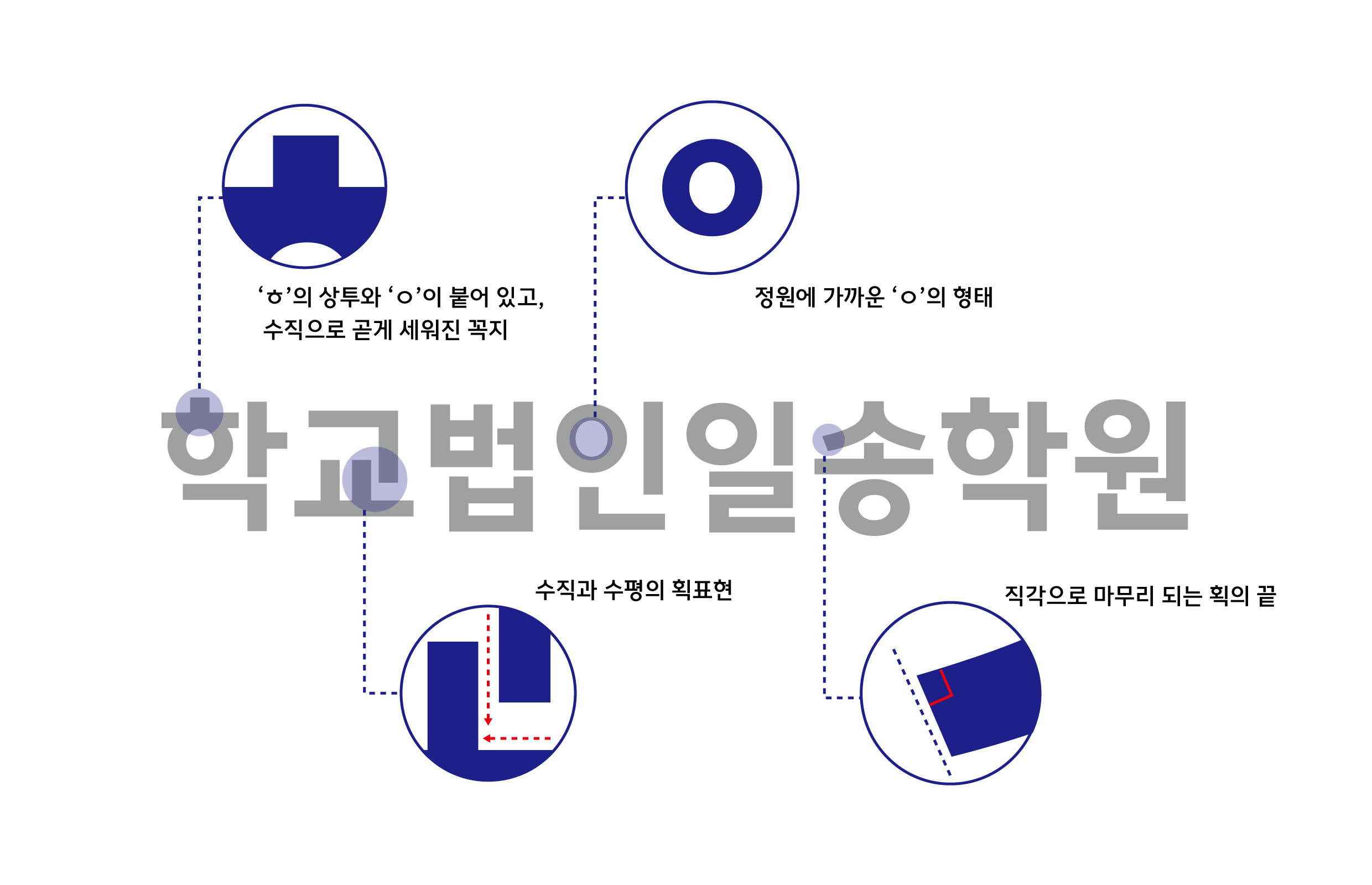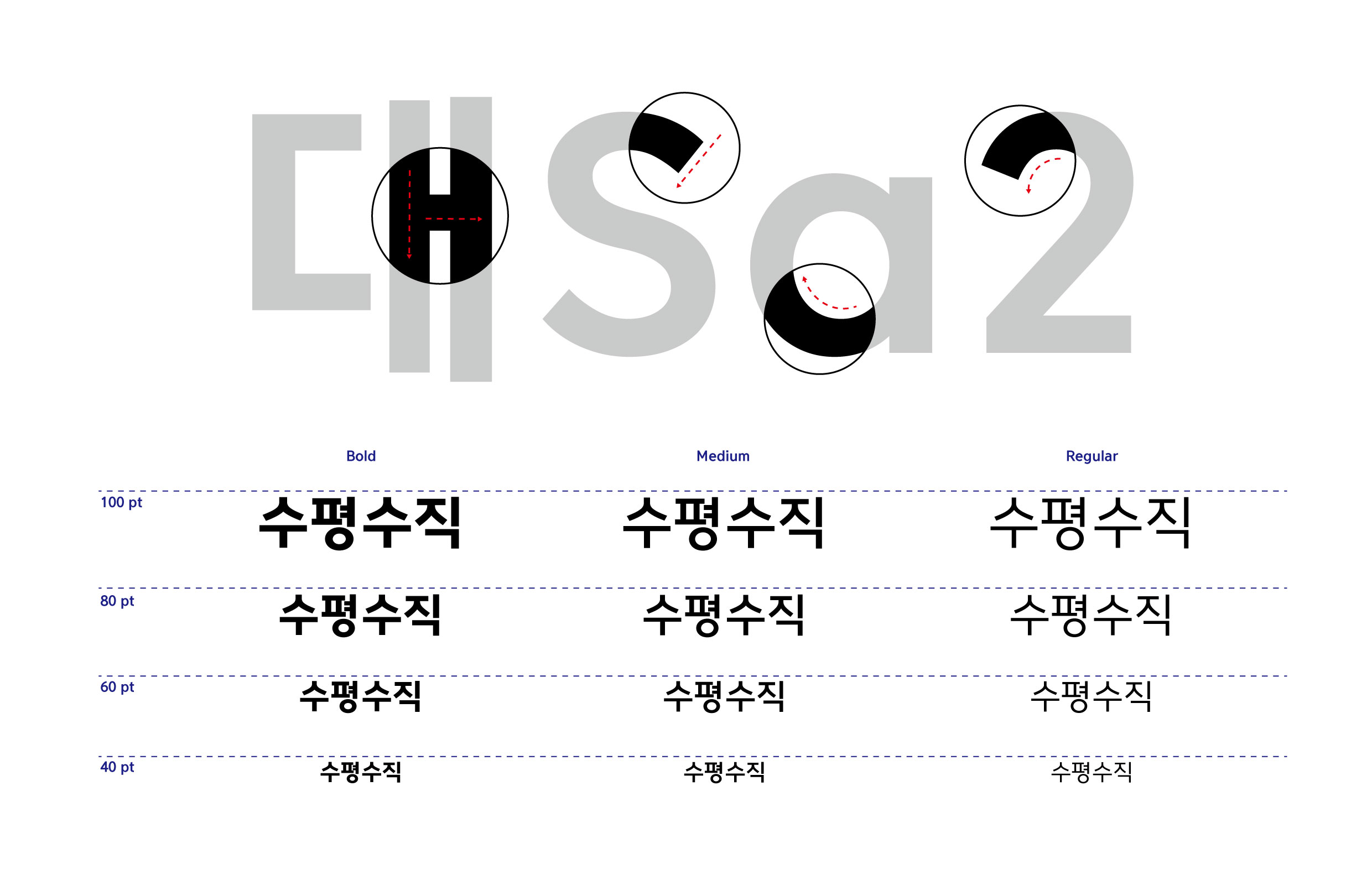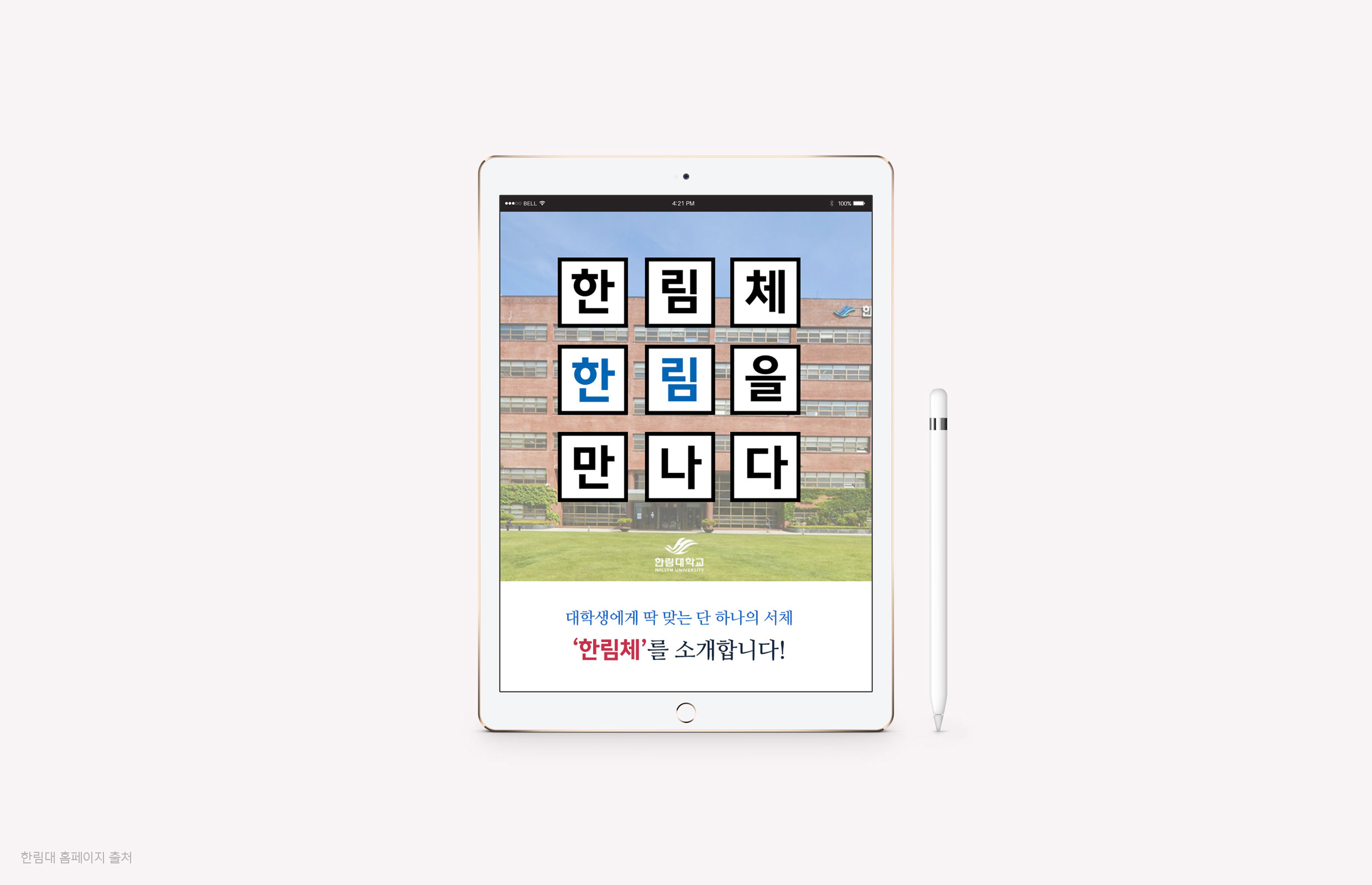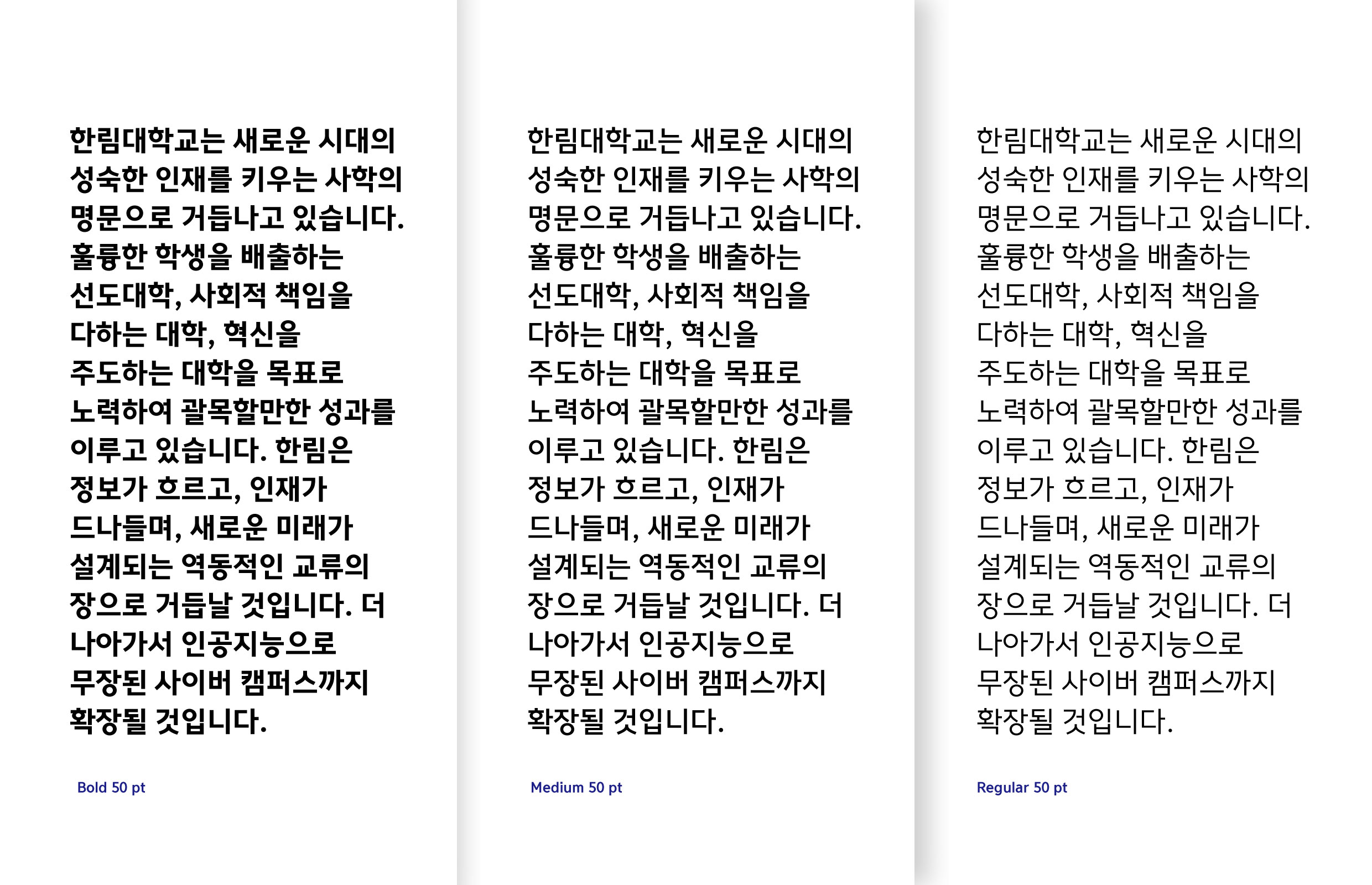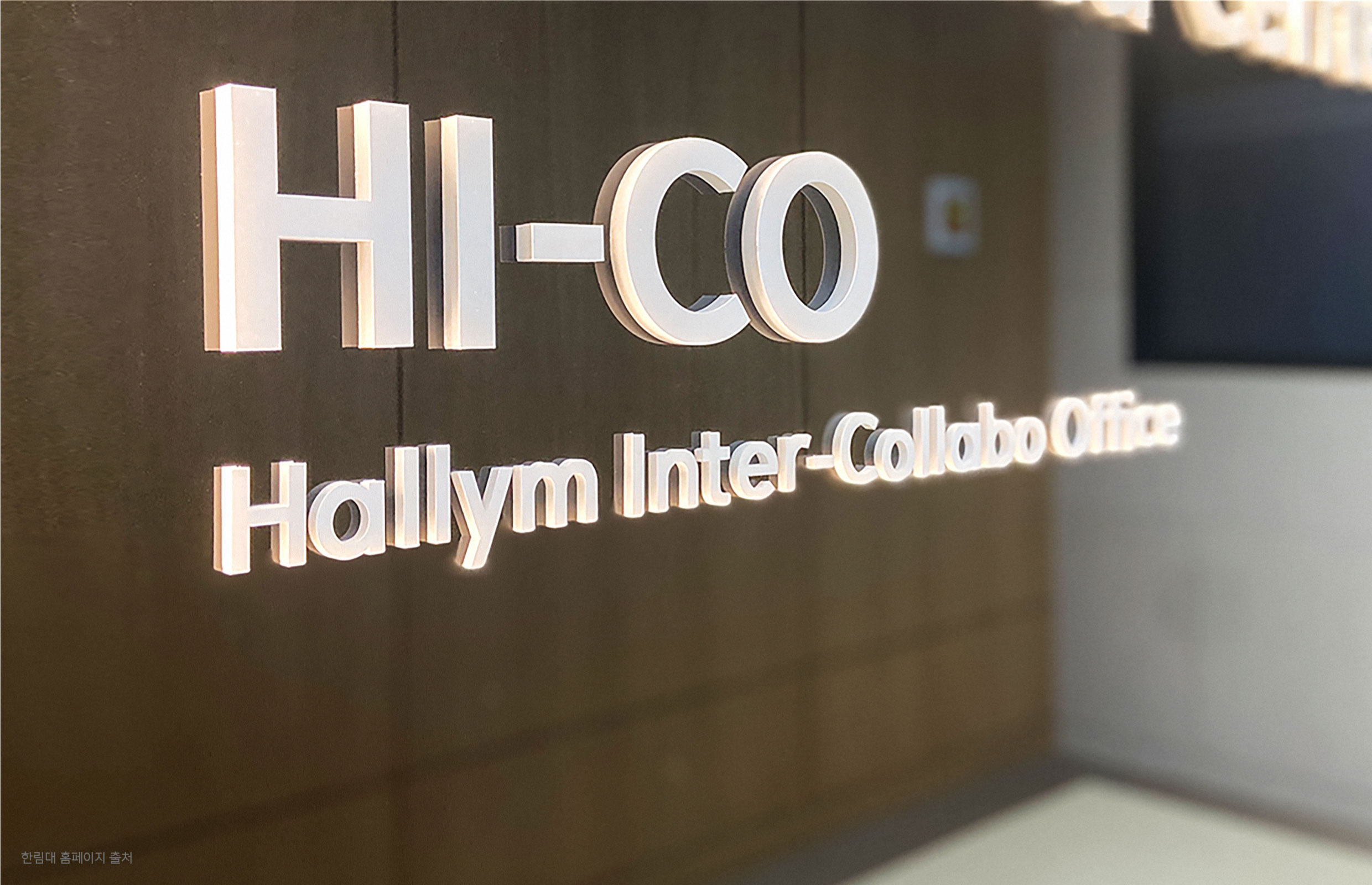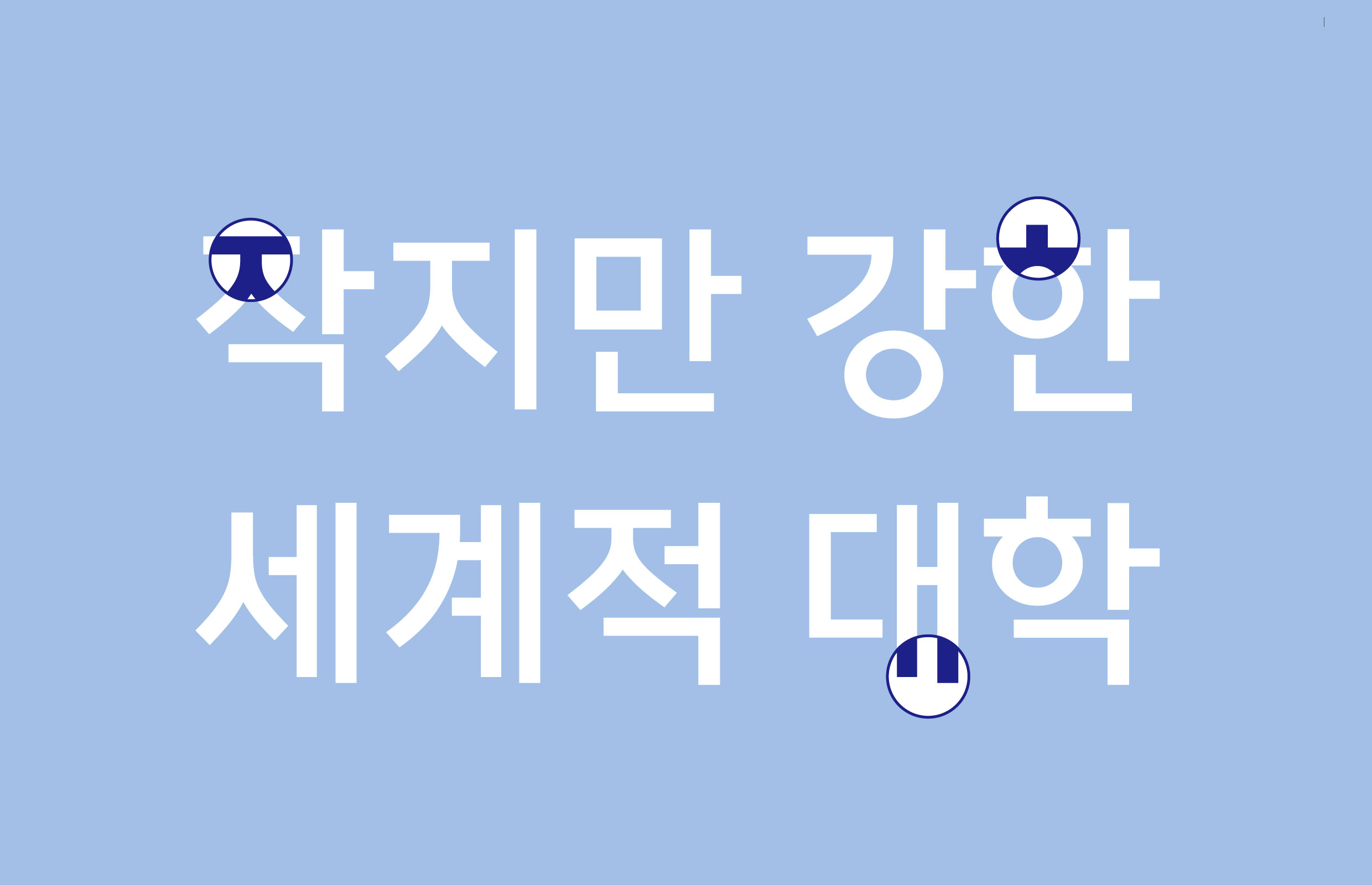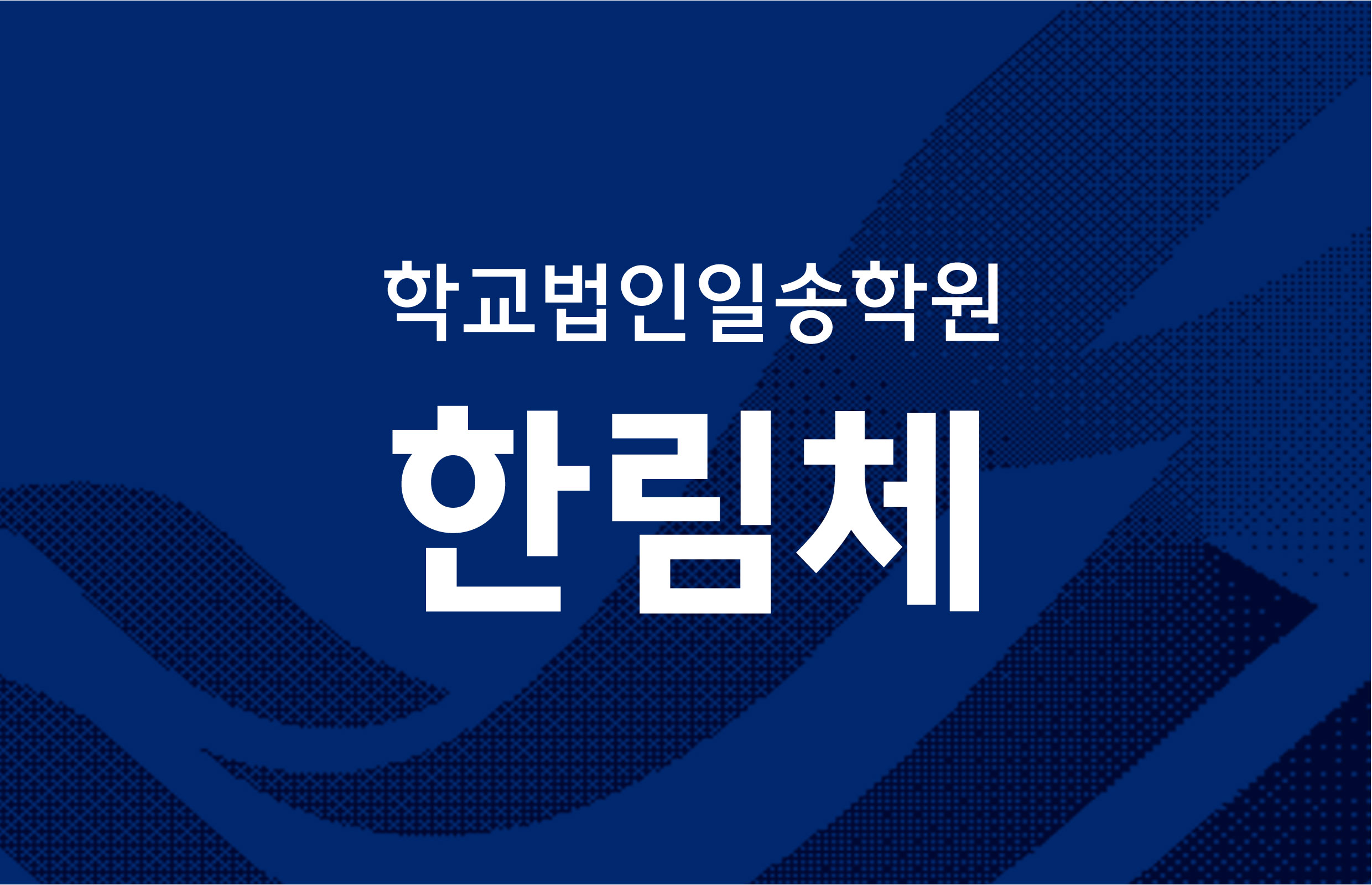
학교법인일송학원 [한림체]
설립자인 고(故) 일송 윤덕선 박사의 탄생 100주년을 기념하여 제작된 학교법인 일송학원 전용서체. 일송의 철학을, 단단하고 안정감 있는 구조와 군더더기 없이 현대적이고 샤프한 자소 형태의 디자인으로 표현했다.
한글 2,780자 / 영문 94자 / KS특수문자 986자